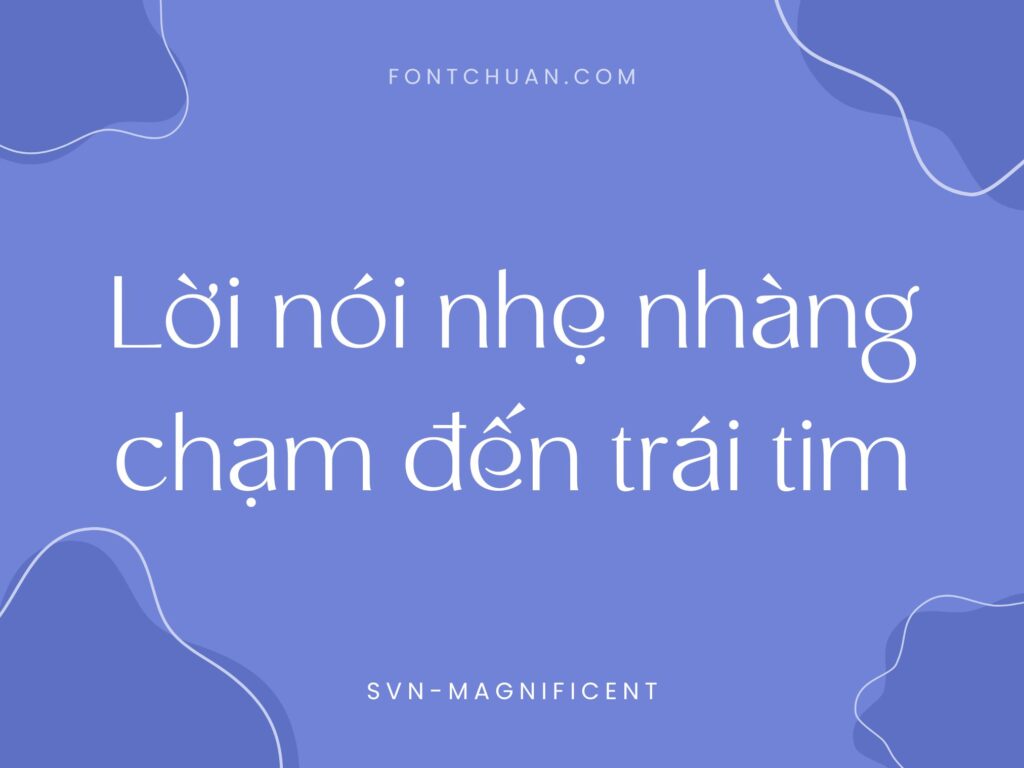
Font SVN Magnificent Việt Hóa
Tác giả Font: Zamroni Hamzah
Font SVN Magnificent là phiên bản Việt hóa của kiểu chữ Magnificent, được thực hiện bởi STYLEno.1 Fonts. Magnificent là một kiểu chữ sans-serif mang phong cách retro nữ tính, kết hợp giữa sự cổ điển và hiện đại. Font này được thiết kế bởi Zamroni Hamzah và phát hành bởi Sensatype. Với các đường nét thanh mảnh và tinh tế, Magnificent mang lại cảm giác sang trọng và thời thượng, phù hợp cho các dự án thiết kế như logo, tiêu đề, bao bì sản phẩm và các ấn phẩm truyền thông. Font bao gồm đầy đủ các ký tự chữ hoa, chữ thường, chữ số và dấu câu, hỗ trợ đa ngôn ngữ.
SVN Magnificent lý tưởng cho các dự án thiết kế yêu cầu sự thanh lịch và hiện đại, như thiết kế logo thương hiệu, tiêu đề tạp chí, bao bì mỹ phẩm và các ấn phẩm truyền thông. Các ngành nghề như quảng cáo, giáo dục và công nghệ có thể tận dụng font này để tạo điểm nhấn trong thiết kế. Ngoài ra, font cũng thích hợp cho các sự kiện như Tết, Giáng sinh, Valentine và các lễ hội khác.